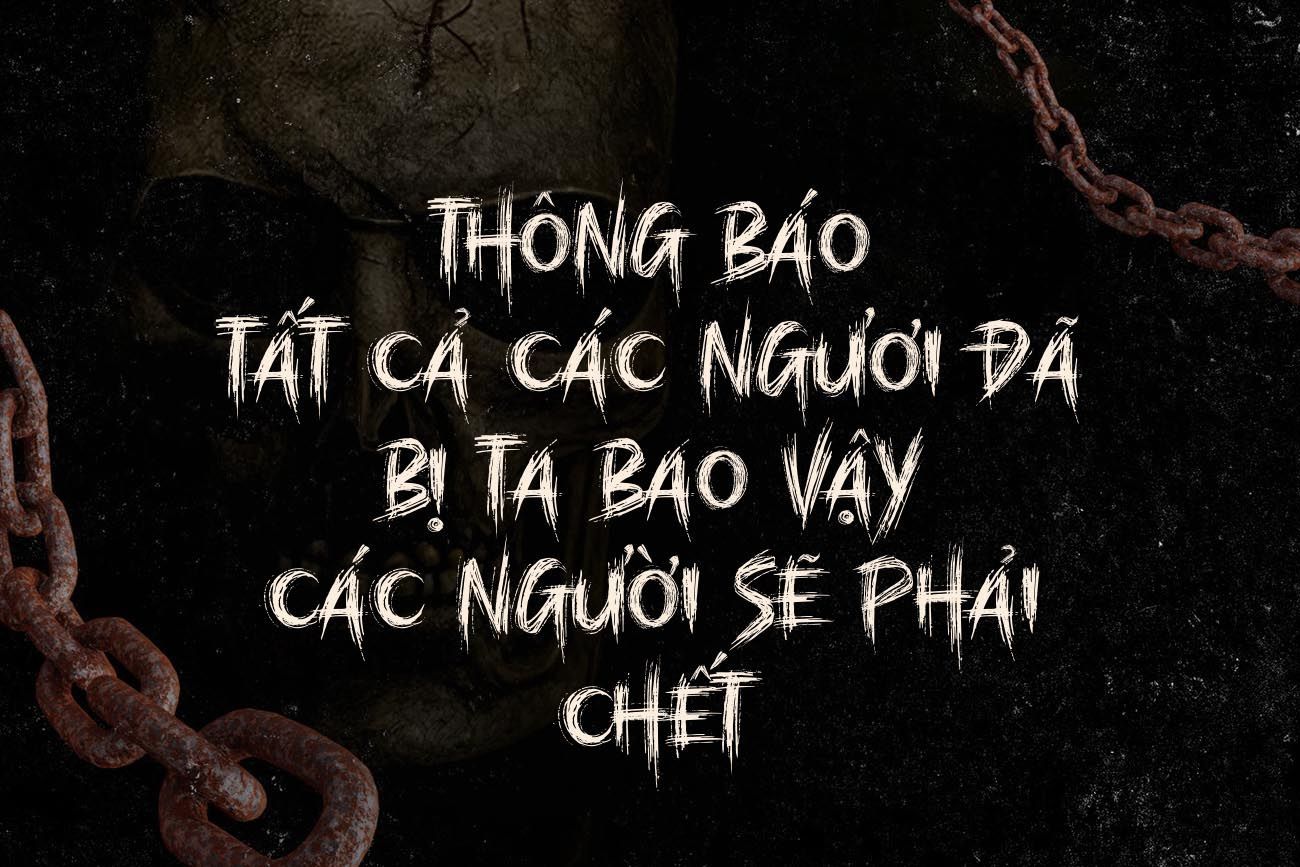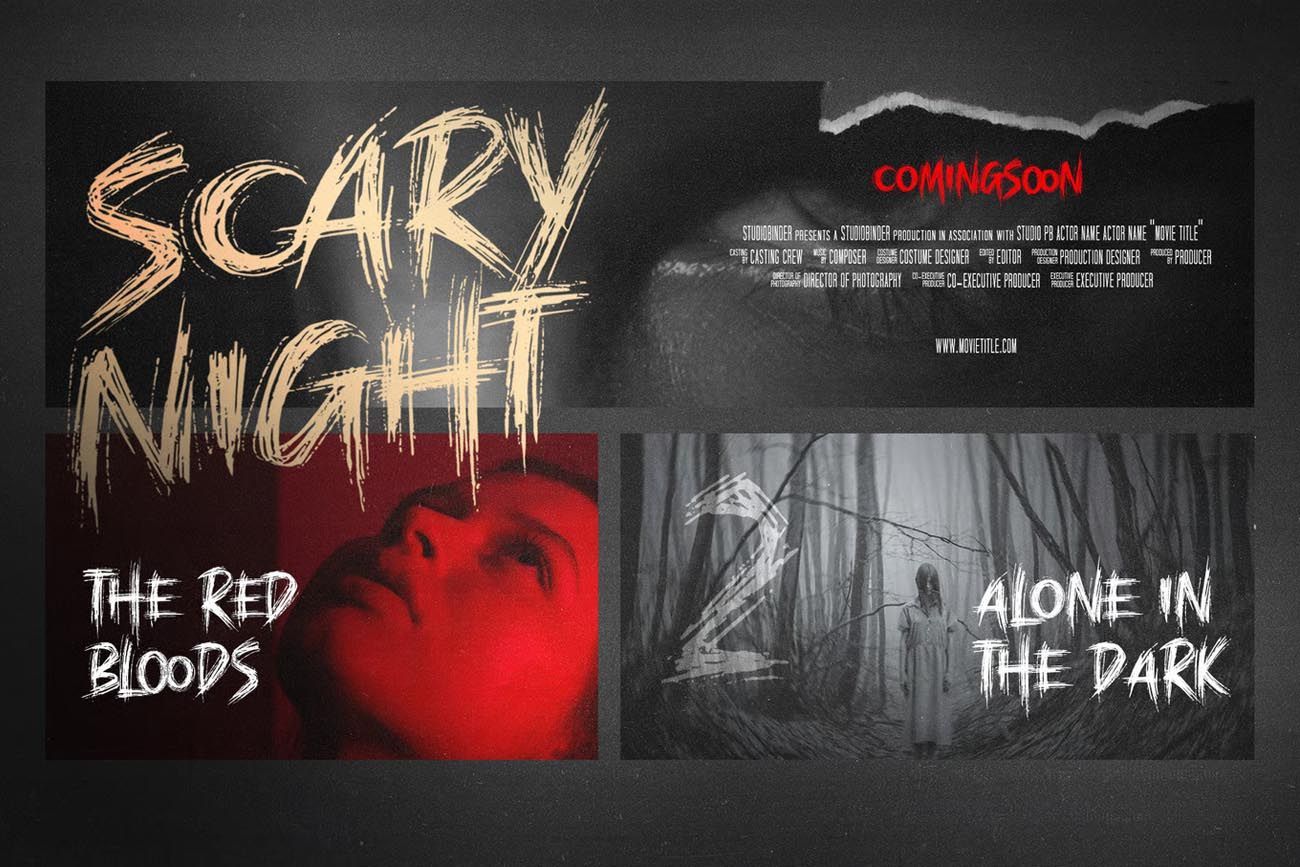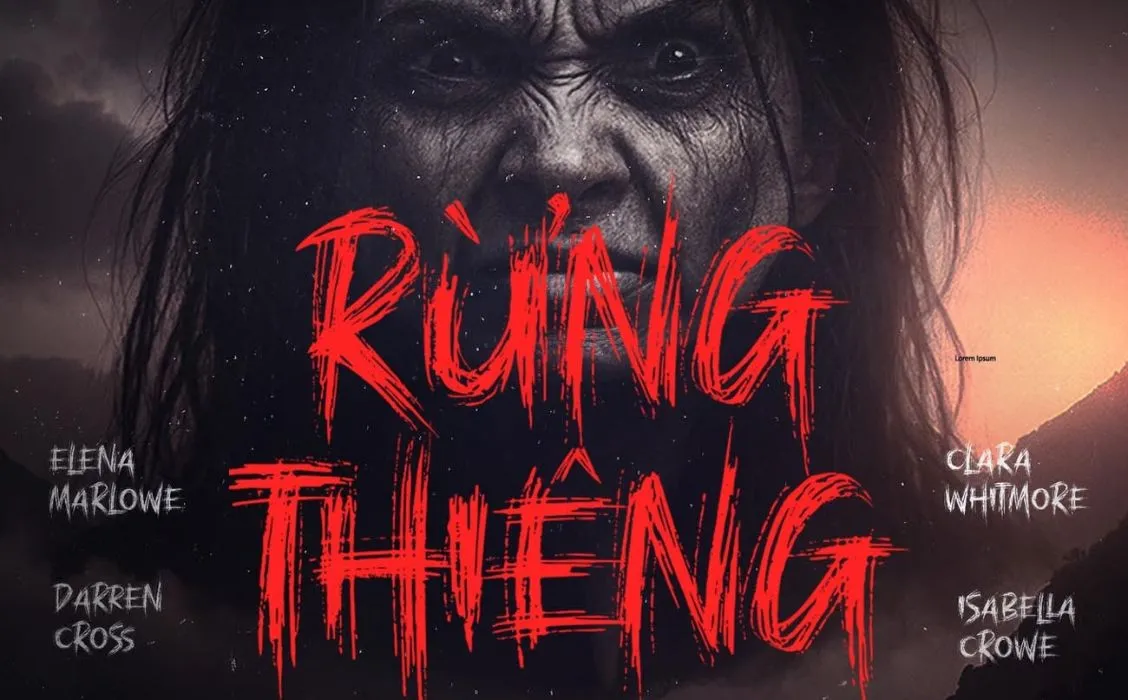
Font chữ Brush kinh dị TH Marching Việt hóa
Font TH Marching Việt hóa chính là một "cơn ác mộng" đầy nghệ thuật dành cho những thiết kế mang hơi hướng giật gân, bí ẩn. Đây là sự lựa chọn không thể thay thế khi bạn muốn truyền tải sự gai góc, nỗi sợ hãi hoặc một chút điên rồ của phong cách Horror Brush.
Bản sắc của bóng tối và sự hỗn loạn
TH Marching không đi theo những quy tắc mềm mại thông thường. Mỗi chữ cái như được vẽ ra từ những nhát cọ khô, những vệt mực dở dang và những đường nét đứt gãy đầy chủ đích. Cấu trúc chữ thô mộc, góc cạnh tạo cảm giác như những dòng chữ được viết vội trên tường trong một bộ phim kinh điển của Hollywood.
Điểm đắt giá nhất của font chữ này chính là sự ám ảnh trong từng chi tiết:
• Hiệu ứng Brush (Cọ vẽ): Các sợi lông cọ để lại vết xước tự nhiên, tạo chiều sâu và độ rung động cho thị giác.
• Cấu trúc phóng khoáng: Các ký tự không đều nhau, mang lại cảm giác hỗn loạn nhưng vẫn giữ được sự cân bằng trong bố cục tổng thể.
Ứng dụng mạnh mẽ cho những ấn phẩm "nặng đô"
Với bản Việt hóa được xử lý chỉn chu, các dấu tiếng Việt không còn là rào cản mà trở thành một phần của sự gai góc. TH Marching là trợ thủ đắc lực cho:
• Poster phim kinh dị: Tạo hiệu ứng rùng rợn ngay từ cái nhìn đầu tiên.
• Bìa sách/Truyện trinh thám: Khơi gợi sự tò mò và kịch tính cho độc giả.
• Thiết kế áo thun Streetwear: Mang lại phong cách bụi bặm, "cháy" và đầy cá tính cho giới trẻ.
• Thumbnail YouTube/Game: Thu hút sự chú ý cực mạnh đối với các nội dung về tâm linh, phá án hoặc hành động.
TH Marching Việt hóa không chỉ là một phông chữ, nó là một tuyên ngôn về phong cách. Nếu bạn đang tìm kiếm một công cụ để kể những câu chuyện giật gân hay những ý tưởng thiết kế phá cách, đây chính là "vũ khí" sắc bén nhất trong bộ sưu tập của bạn.